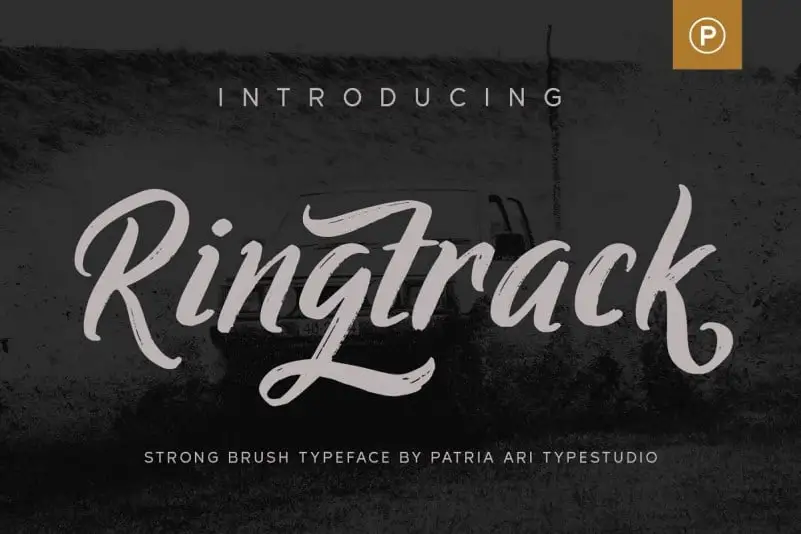
Ringtrack Brush Font – Fonte Grátis
Ringtrack Brush Font
Ringtrack Brush Font é uma fonte script moderna que oferece um tom elegante e envolvente para qualquer projeto visual. Inspirada na escrita áspera e elegante das ruas de uma cidade, a Ringtrack captura o espírito urbano com seu traçado fluido e dinâmico. Este design foi projetado para simplificar o processo de criação gráfica, facilitando o uso em diversas aplicações como branding, roupas, logotipos, postagens nas redes sociais, anúncios e embalagens. É perfeitamente adaptável a um vasto leque de projetos, desde identidades corporativas até designs para produtos e selos. Seu estilo fluido permite que você desenvolva trabalhos com criatividade e personalidade, tornando suas criações ainda mais atraentes e memoráveis. A Ringtrack Brush Font é uma excelente escolha para designers atentos à qualidade visual, sempre buscando manter seu trabalho ao nível superior. Sua simplicidade na utilização combina perfeitamente com o desejado resultado de alta qualidade, tornando-a um recurso indispensável em qualquer estante de fontes.